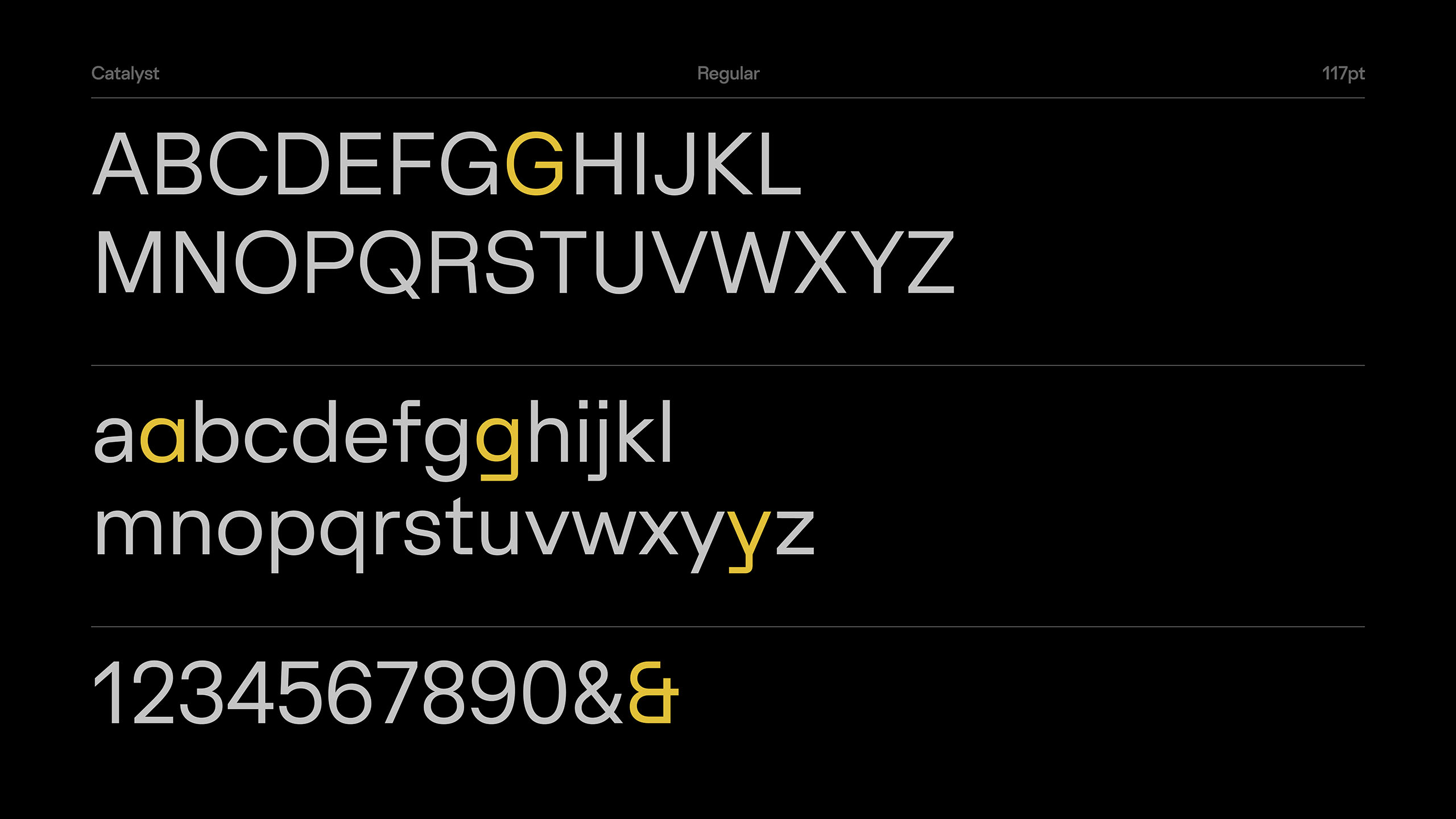
Catalyst 是由站酷网友 Yooooh_(UID:20087263) 设计的一款开源免费商用英文字体。
Catalyst 字体风格现代、简洁、稳重,适用于各种场景,是一款无衬线双轴可变英文字库,有7款字重,14款样式,552个字形,包含静态版本TTF、OTF、WOFF、WOFF2以及可变版本。